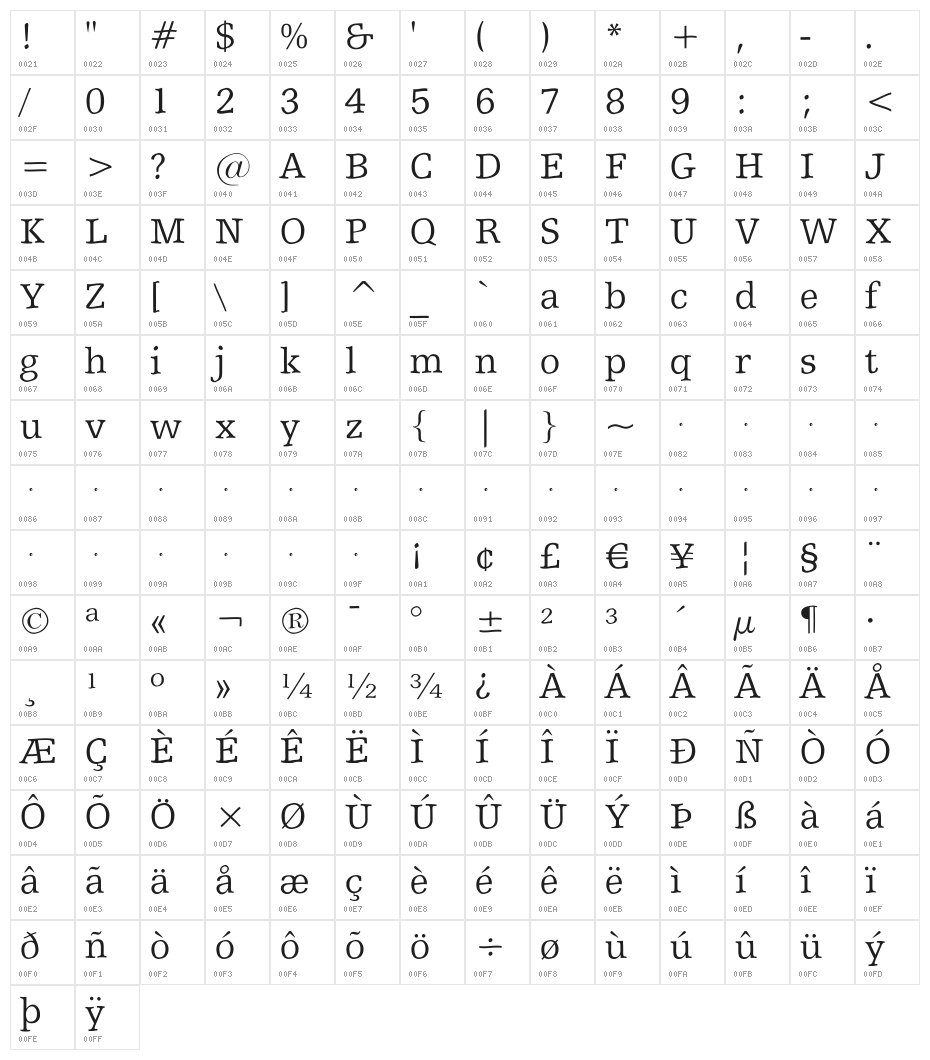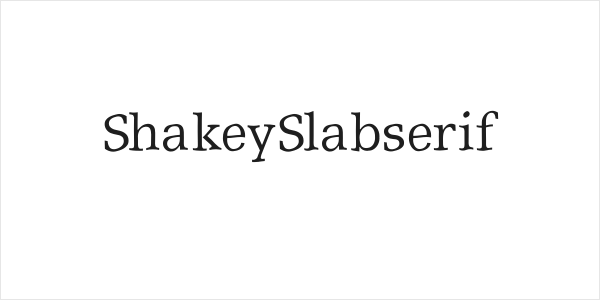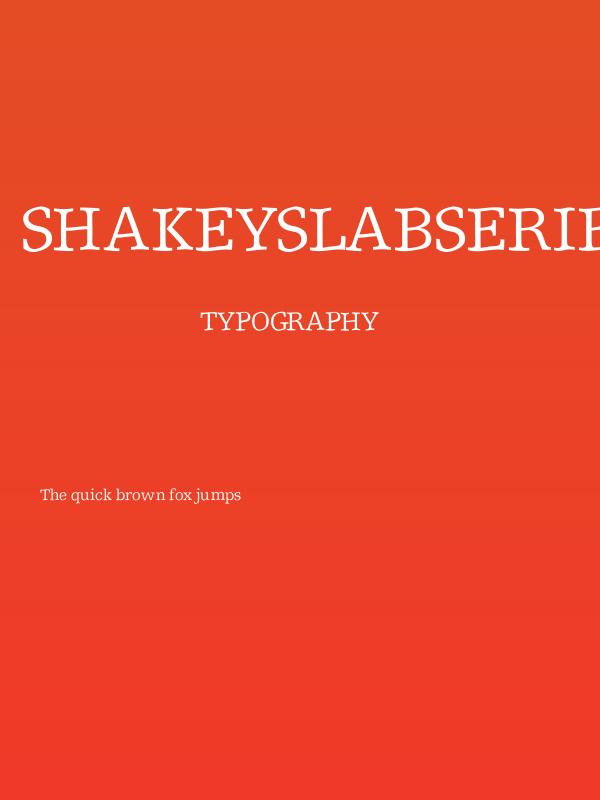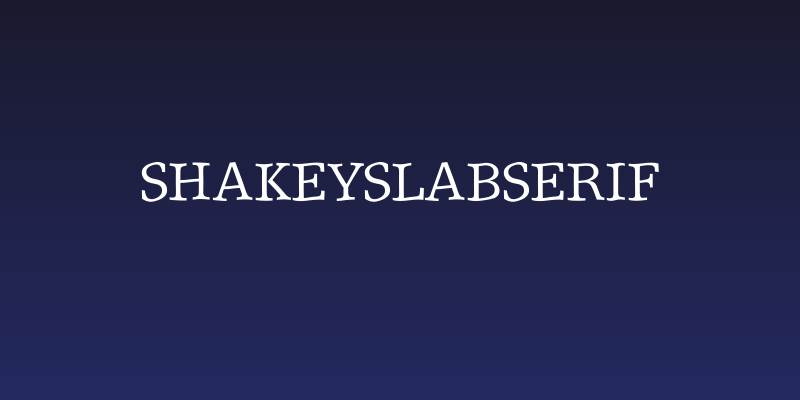
ShakeySlabserif Font
| Caso d'uso | Headlines, Logos, Editorial Design |
| Progetti proposti | Ideal for branding, editorial design, posters, and packaging that require a classic yet modern touch. |